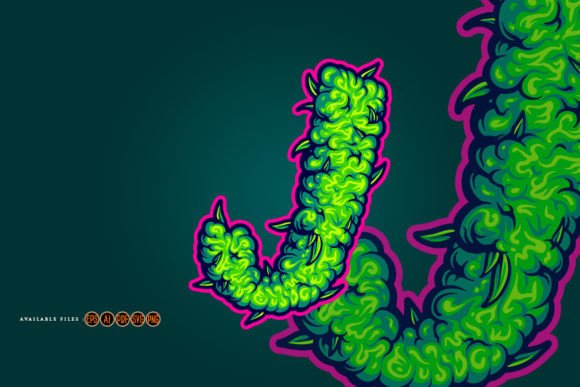
Intriguing Monogram Letter Initial J
Ul‑a‑s‑ã‑nte do Monograma J com Textura de Cannabis – Detalhes que Encantam
Se você está em busca de um design exclusivo para turbinar seus produtos, o Intriguing Monogram Letter Initial J é a escolha ideal. Este monograma combina a elegância da letra “J” com a ousadia de uma textura realista de bud de cannabis, criando um visual que se destaca em qualquer aplicação.
Por que este monograma é perfeito para o seu projeto?
- Versatilidade total: ideal para camisetas, tote bags, adesivos, banners, cartões, flyers, pôsteres e muito mais.
Benefícios de usar este monograma em seus produtos
Com o Monograma J, você ganha:
- Impacto visual imediato – a combinação de tipografia clássica e textura de cannabis cria curiosidade e atrai olhares.
- Flexibilidade de aplicação – use em produtos físicos e digitais sem precisar recriar o artwork.